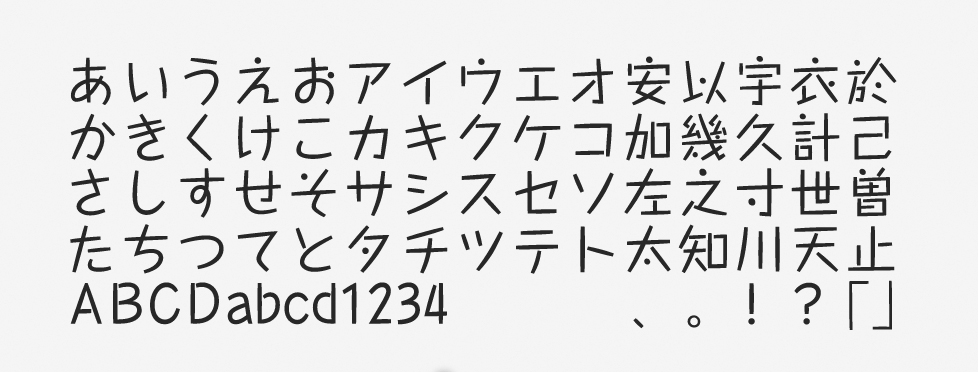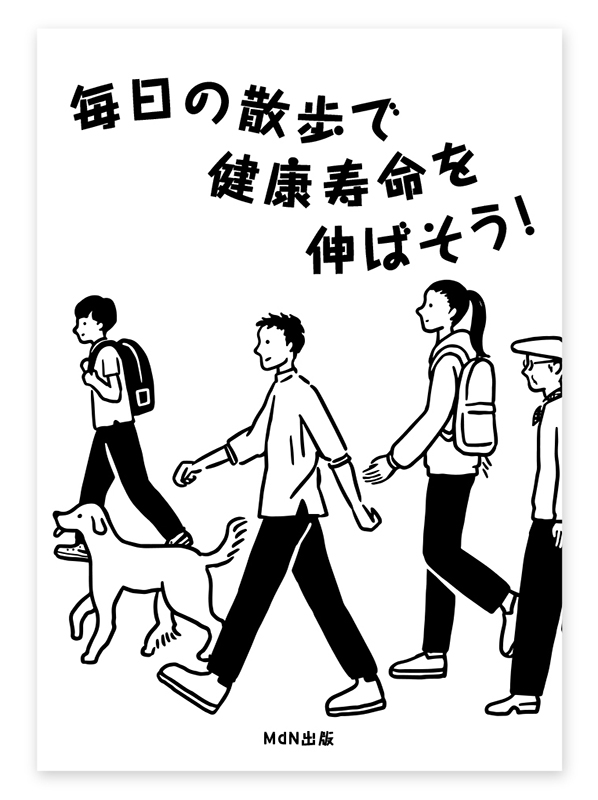
「タカハンド」について
タカハンドは、たかデザインプロダクションの高原新一氏が手掛けた「タカ書体」の1つです。モリサワからは、まず1987年に写植用(※1)の文字として発売されました。その後はDTP用のフォントにもなり、ディスプレイや見出しやタイトルなど、さまざまな場面で個性的なフリーハンドスタイルのフォントとして活用されています。
「タカハンド」の特徴
膨らみのあるストロークとドット型のエレメントが特徴で、非常に個性的なデザイン書体です。ほのぼのとした温かみやリズム感を表現でき、明るくて親しみやすい雰囲気を出したいときには特に効果的です。
クセが強いフォントであるため、デザインの一部分のみで使用し、アクセントとして扱っても効果的でしょう。手書きをイメージさせ、まるで楽しげに語りかけてくるような身近な雰囲気も感じさせます。
タカハンドは、ほのぼの、のんき、ポップといったキーワードを彷彿させます。作例で使用したウエイトHは、かなり太めのラインで構成されているので、タイトルや見出しなど大きめサイズでの使用が効果的です。ウエイト展開はL、M、DB、B、Hと5つあり、細いウエイトではキャプションなどでの利用もおすすめです。